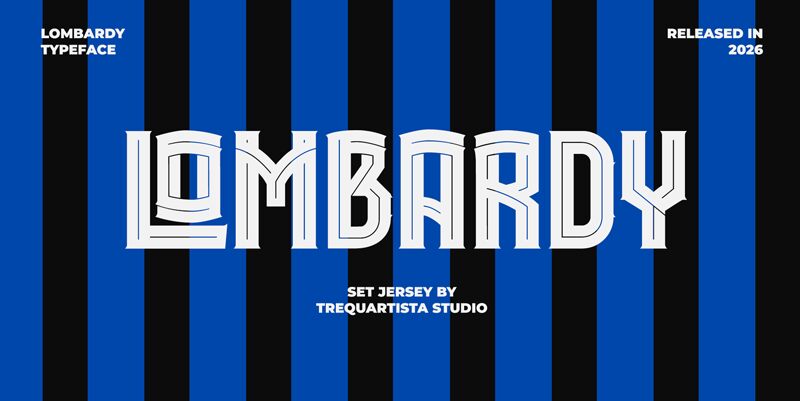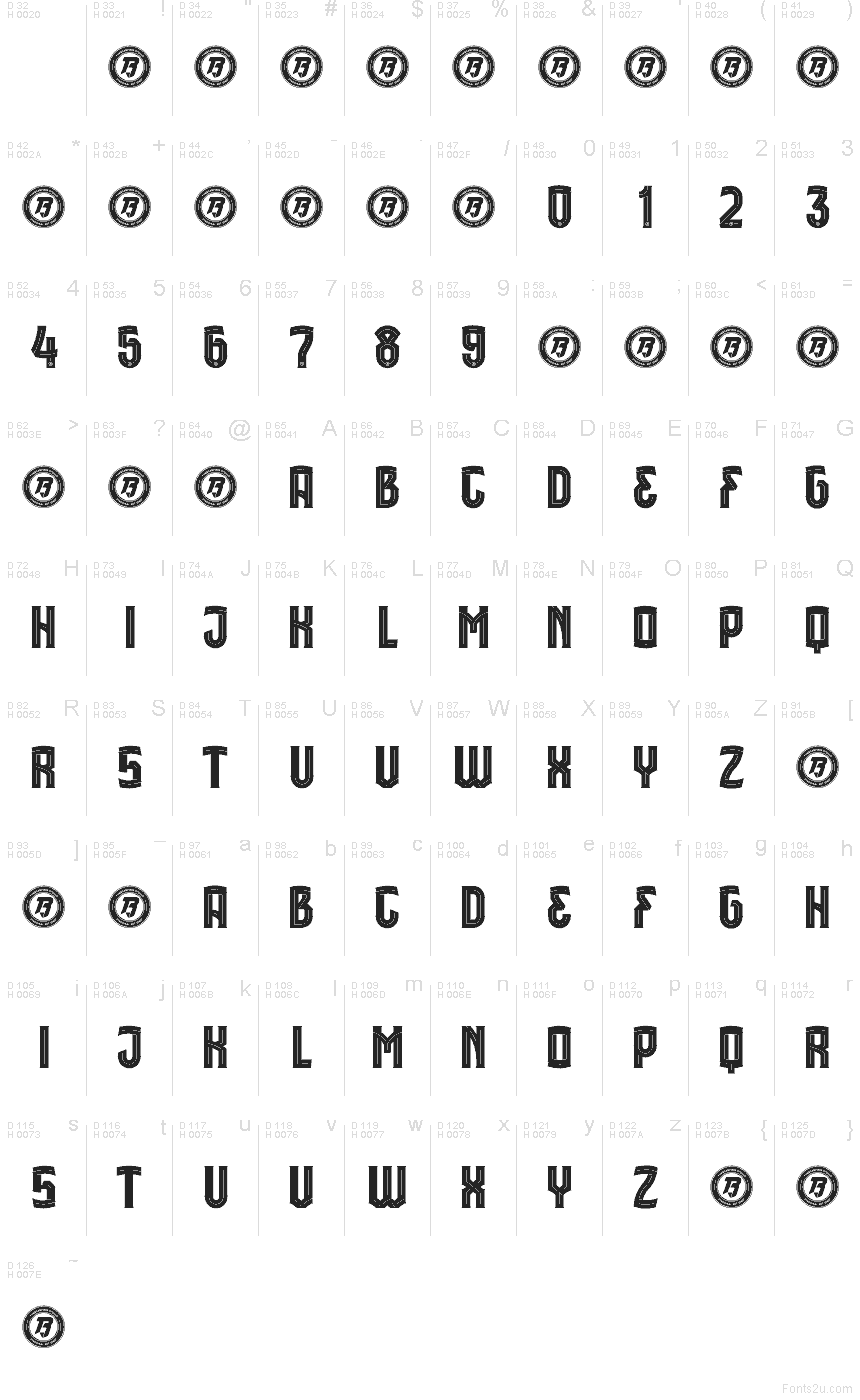
Lombardy od Trequartista Studio to darmowy, akcydensowy krój pisma w stylu Art Déco. Wysokie wersaliki, łukowate zwieńczenia i wpuszczane linie nadają literom klimat plakatów dawnej epoki. Powtarzająca się mieszanka kwadratowych pionów i zaokrąglonych, wewnętrznych detali sprawia, że font jest architektoniczny, a zarazem efektowny, z teatralnym rytmem, który płynie przez cały tekst.
Idealnie pasuje do brandingu barów i krawców, plakatów imprezowych, opakowań retro, tytułów w czasopismach i plansz tytułowych, gdzie potrzeba stylizowanego sznytu lat 20. Jako darmowy font, Lombardy świetnie sprawdza się też w monogramach i inicjałach – warstwowe kontury i wysokie szczyty liter nadają nawet krótkim napisom gotową ramę.